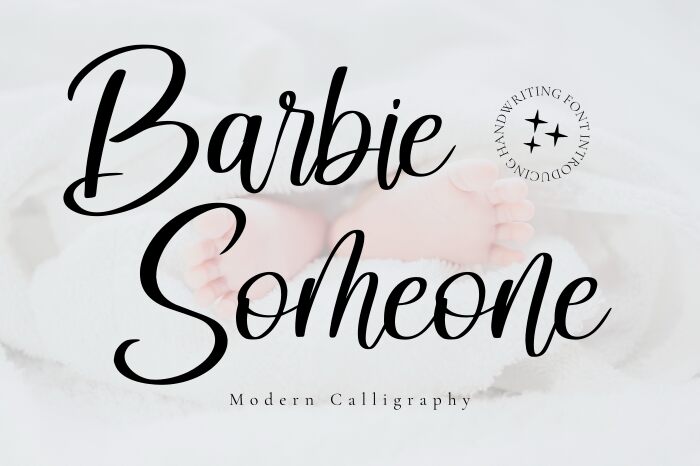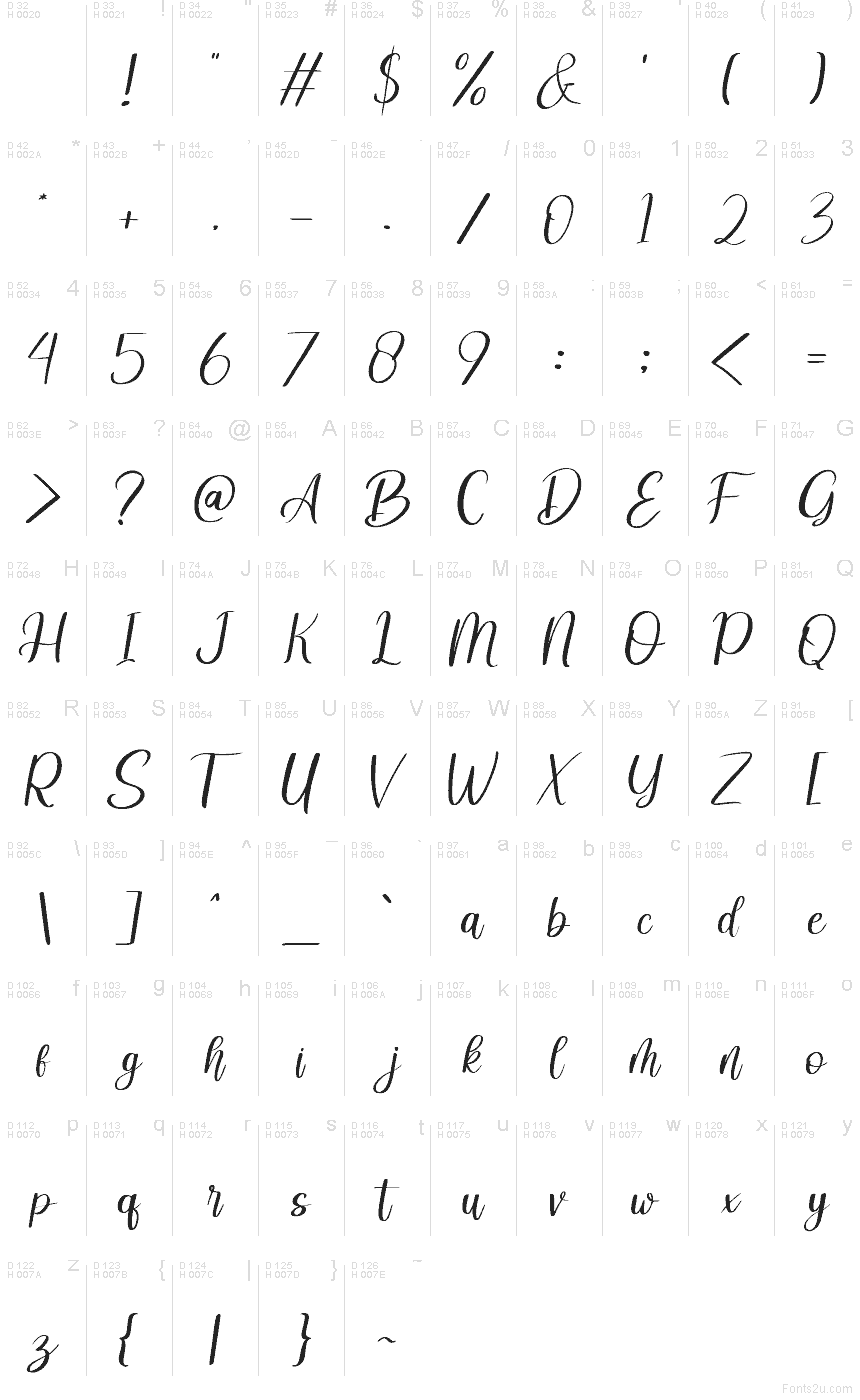
Barbie SomeOne de Rissyletter Studio es una tipografía caligráfica moderna y gratuita con un aire ligero y muy a la moda. Las letras se mueven con curvas largas y brillantes y un ritmo esbelto; las grandes florituras iniciales y las uniones finas le dan a toda la fuente una fluidez aérea, casi como una firma.
Es ideal para branding de boutiques, empaques de belleza, encabezados de invitaciones, portadas de revistas y títulos en redes sociales donde un estilo manuscrito elegante marca la diferencia. Al ser una tipografía gratuita, también funciona muy bien en logotipos cortos y monogramas, ya que esos trazos de entrada y salida extendidos le dan a cualquier palabra una sensación personal y sofisticada.